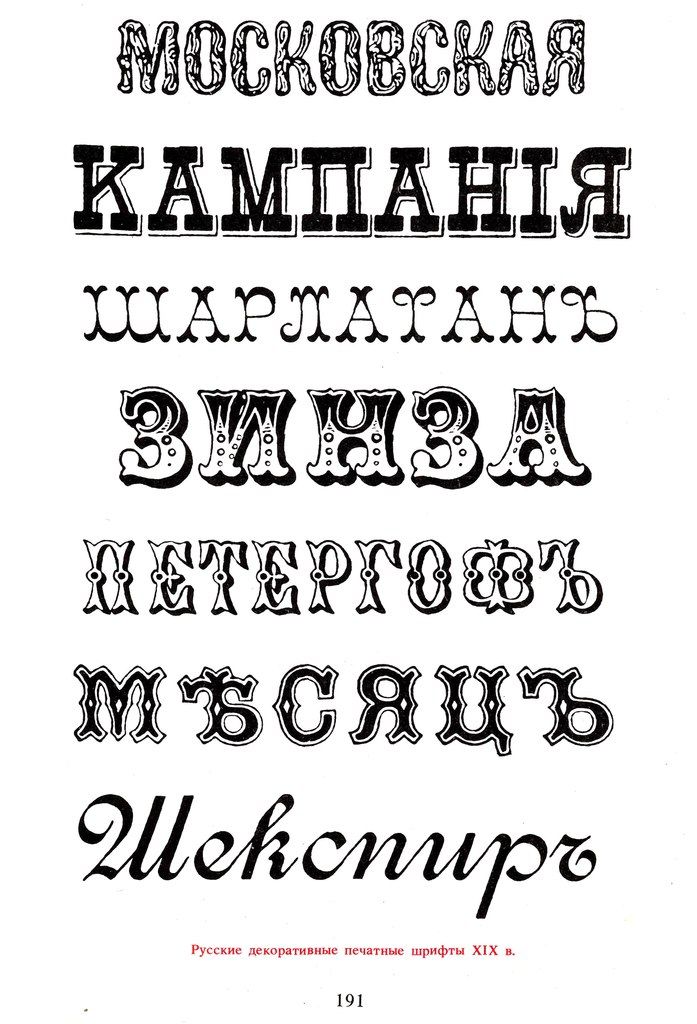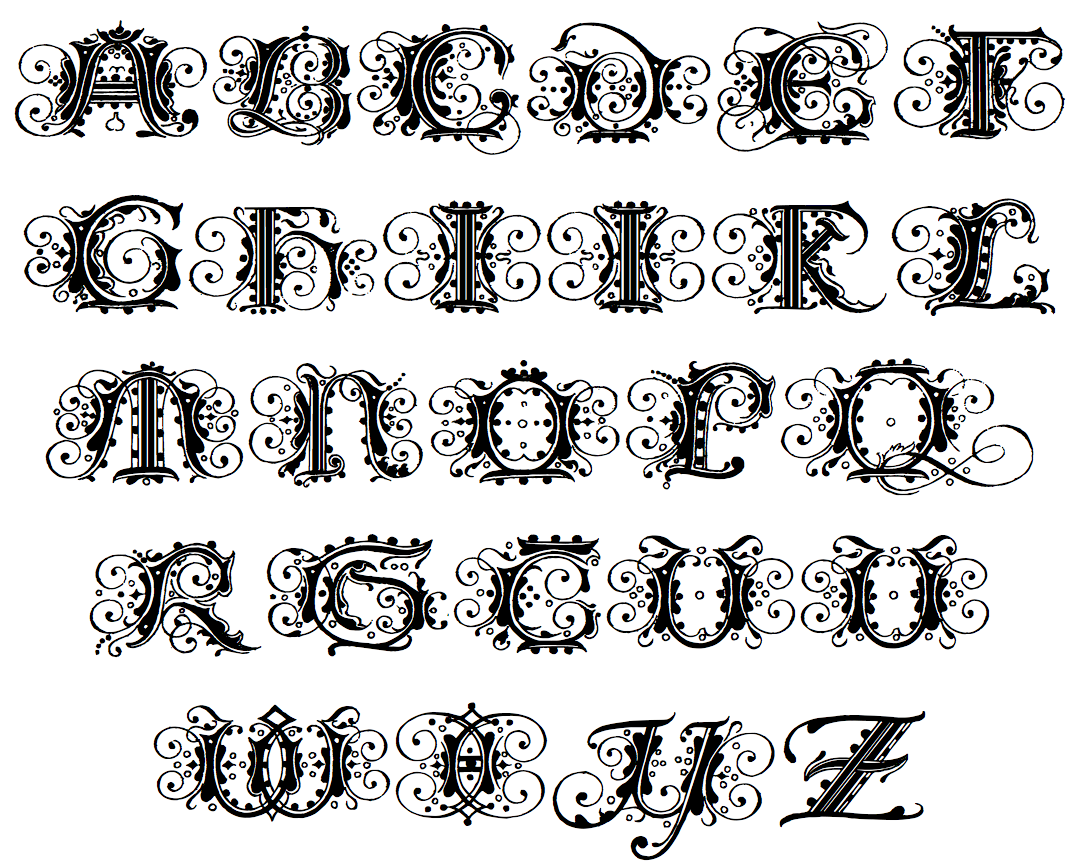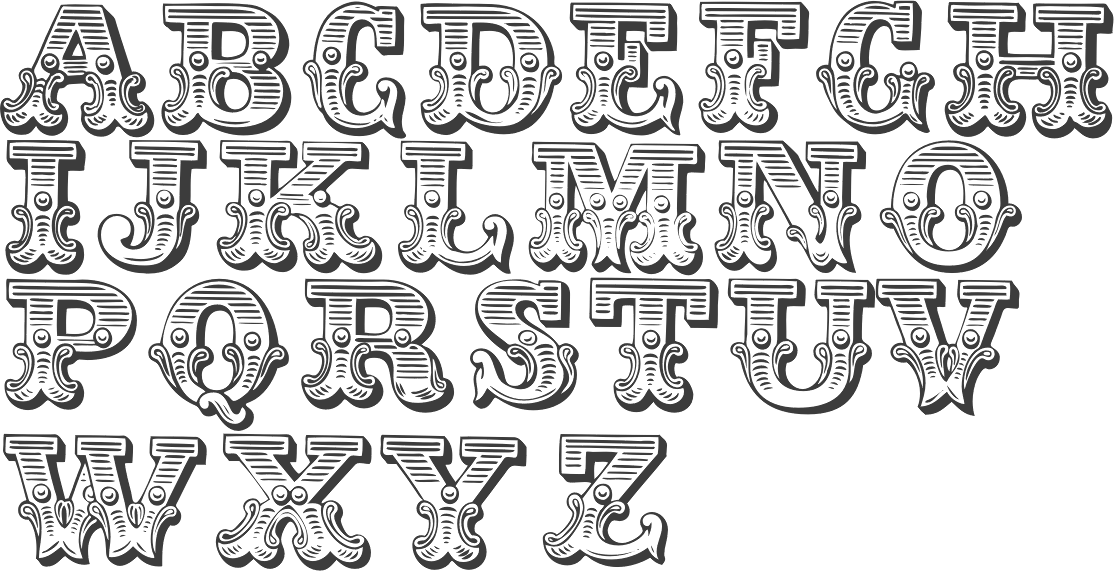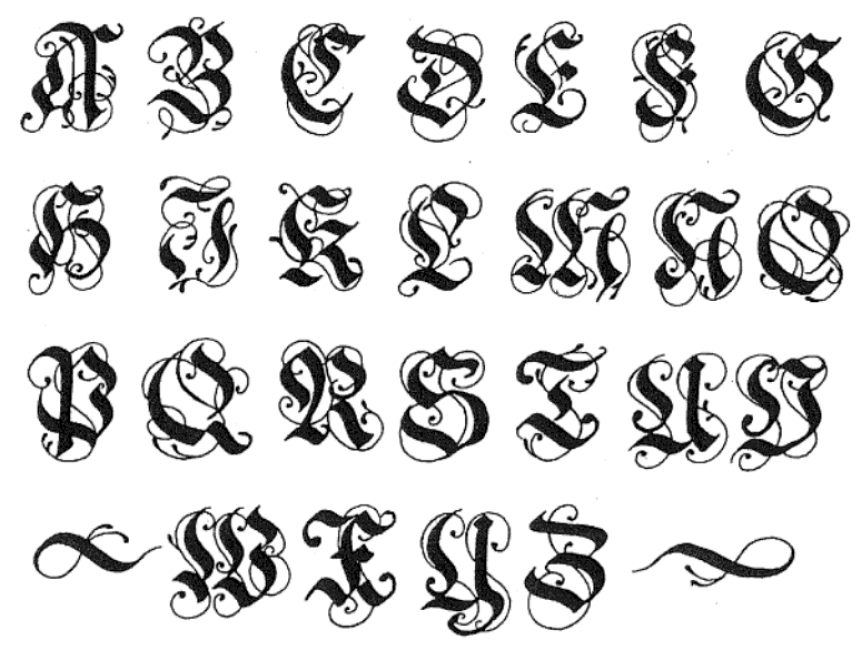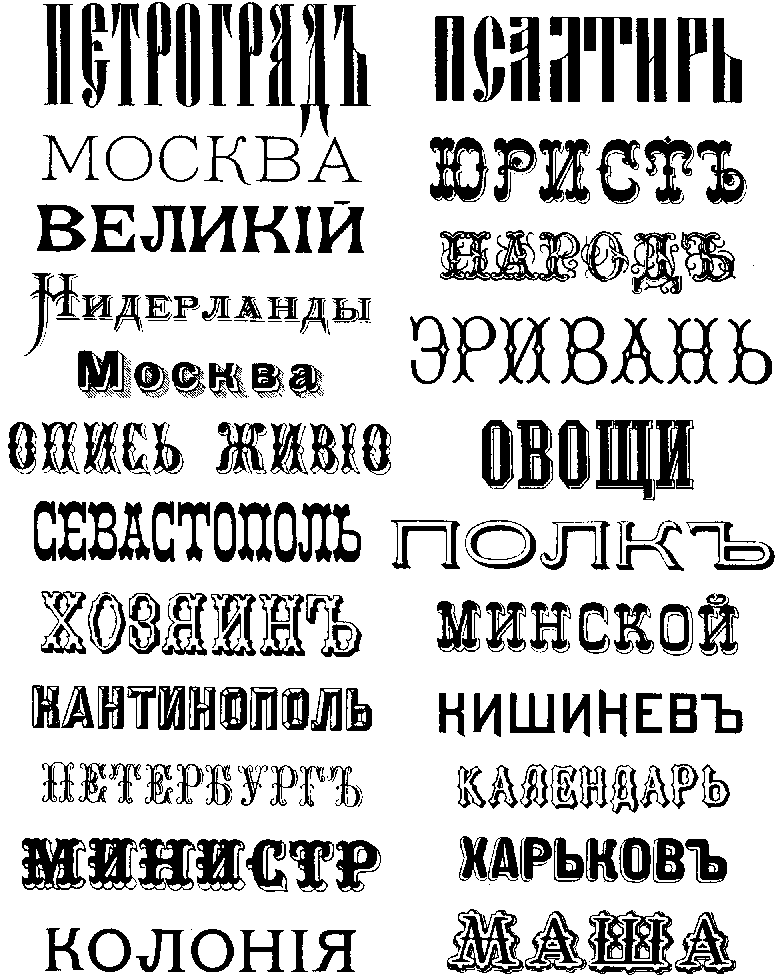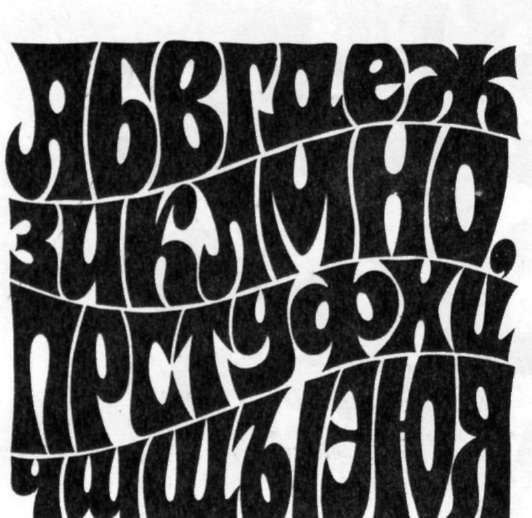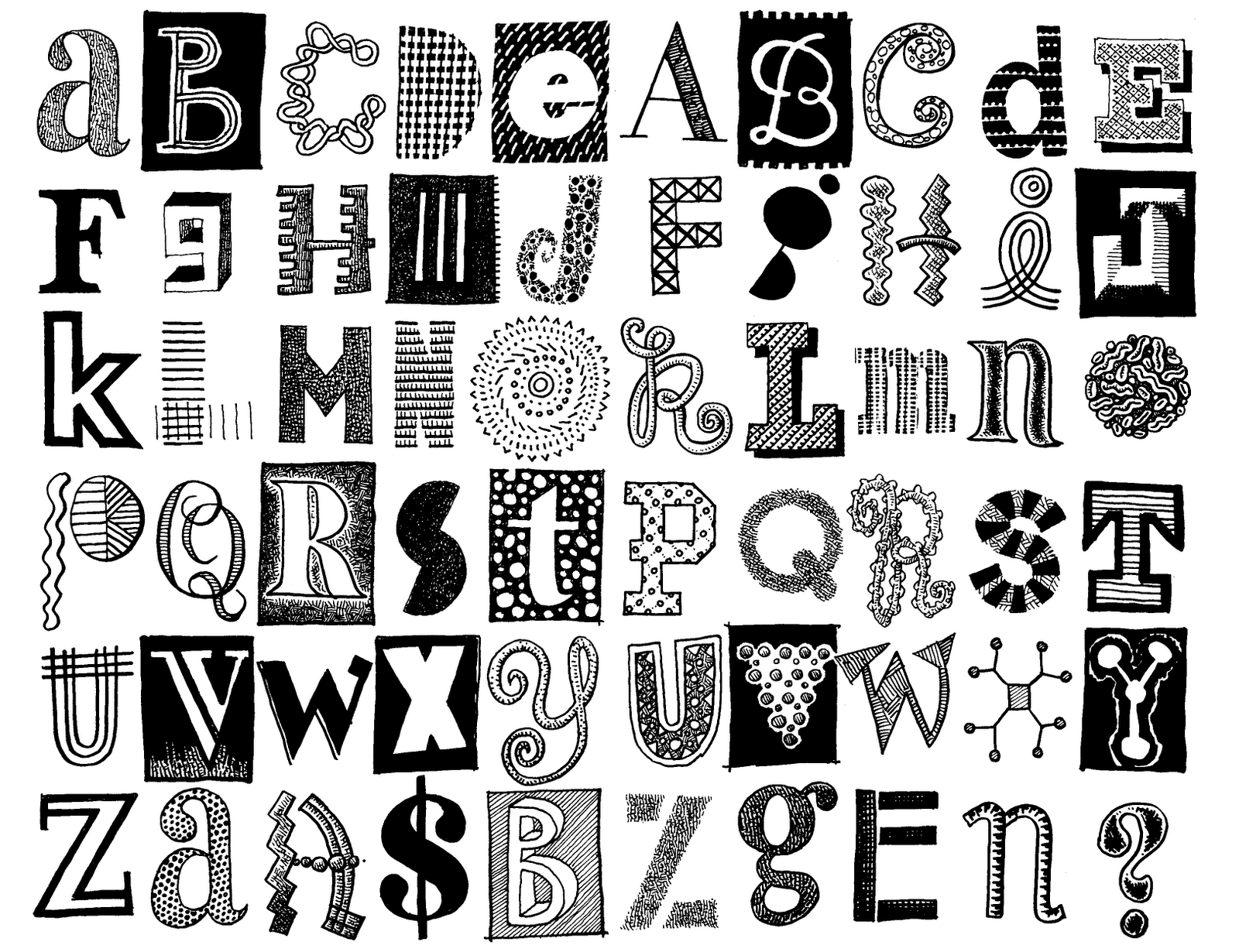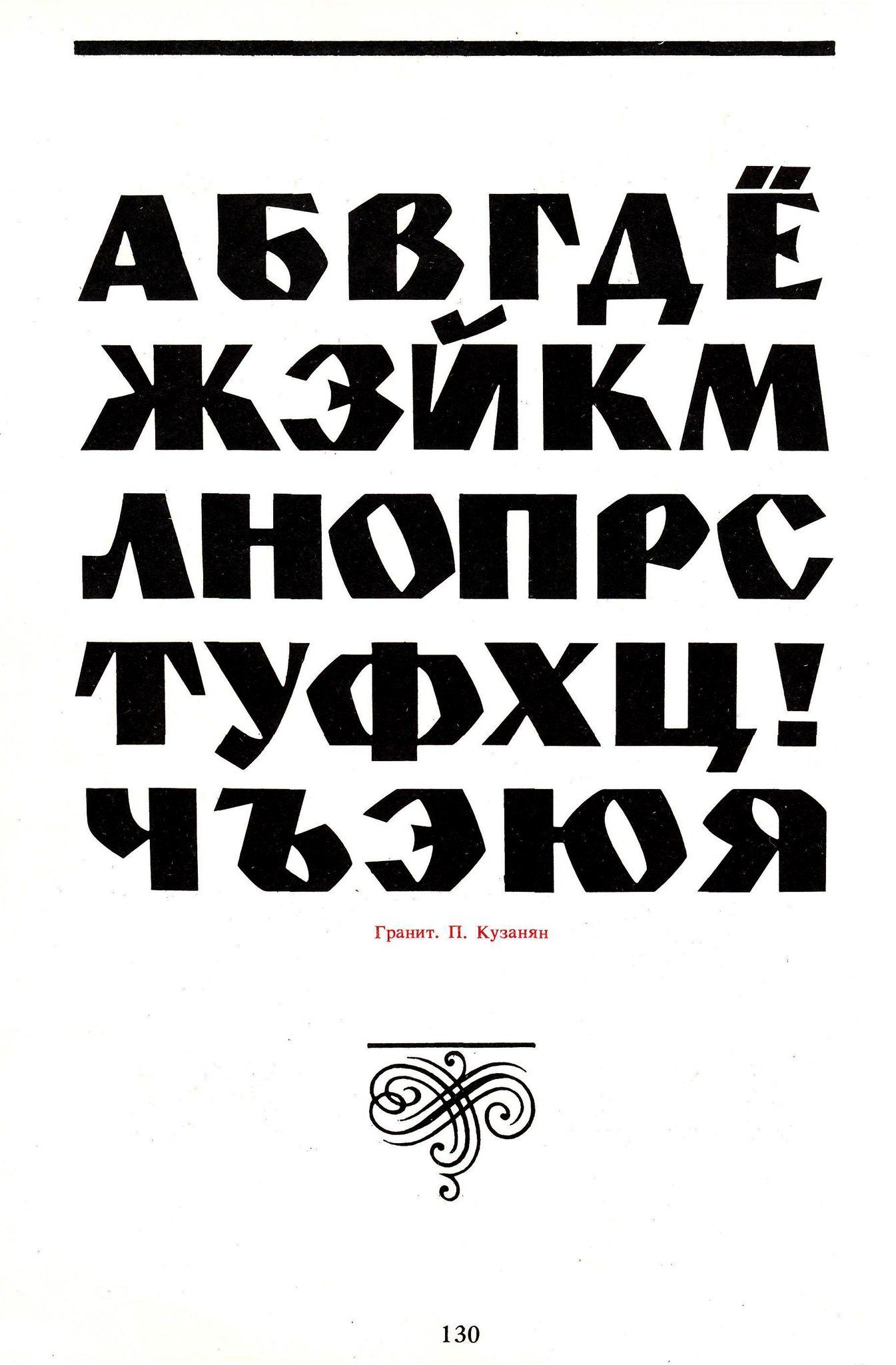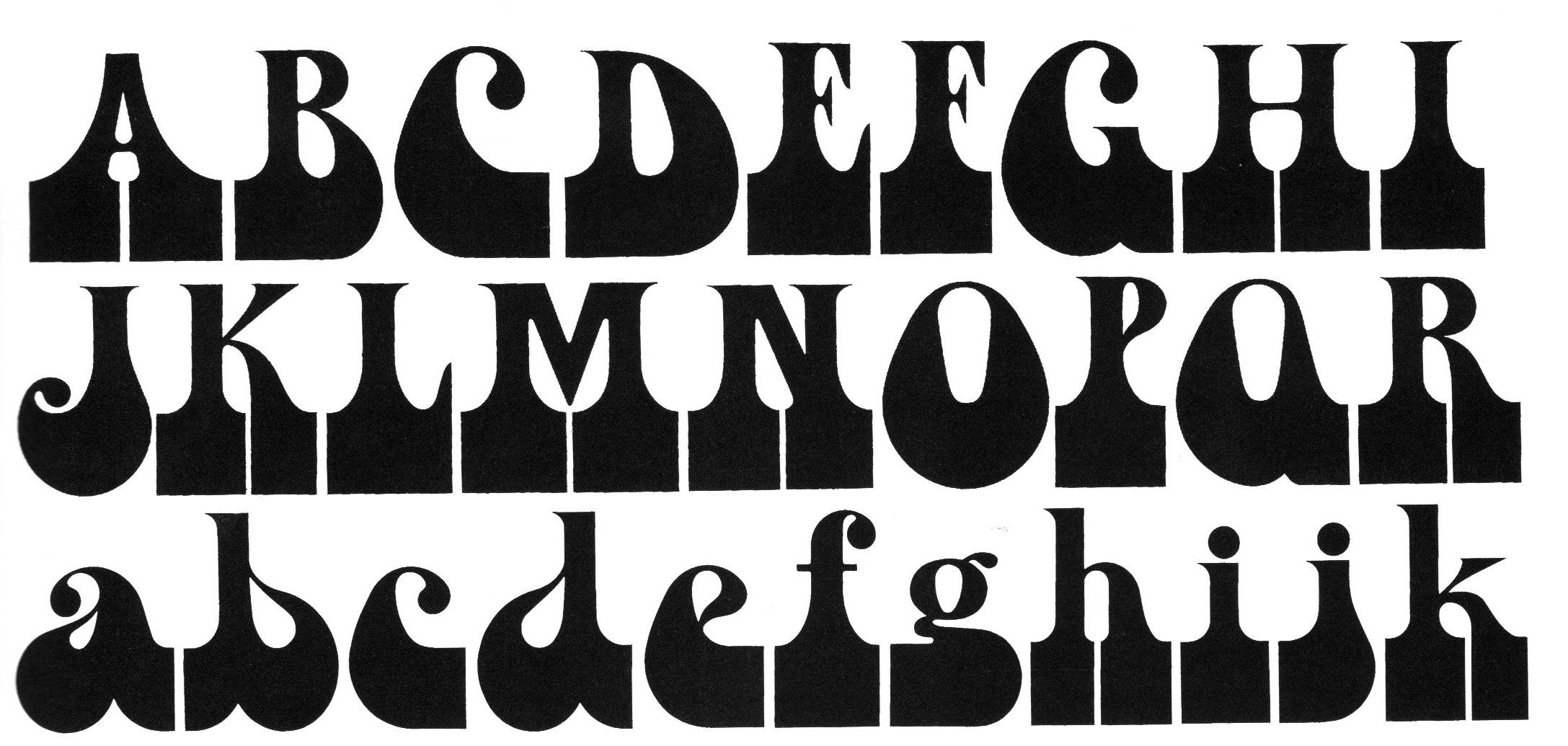
Шрифты оформительские: Декоративные шрифты для художественно-оформительских работ
Шрифты-алфавиты для рекламных и декоративно-оформительских работ 7
Курсив декоративный, с наклонными соединительными штрихами —
стр.
121
Курсив рекламный (переложение латинского шрифта Р. Шпигеля) —
стр. 122
Инициалы: а — по В. Тоотсу; б — декоративные по Р. Шпигелю —
стр. 123
Курсив «шнурковый» (переложение латинского шрифта В. Шенка) —
стр. 124
Шрифт декоративный для исполнения колонковыми кистями
(переложение латинского шрифта) — стр. 125
Курсив рукописный Б. Воронецкого — стр. 126
Шрифты рубленые типа гротесковых и брусковых
Шрифт плакатный, рубленый, прямой, светлый — стр. 127
Шрифт нормальный, рубленый, узкий (по В. Шенку) — стр. 128
Шрифт плакатный, жирный — стр. 129
Шрифт рубленый, прямой, узкий, светлый — стр. 130
Шрифт плакатный, нормальный, прямой, узкий, с овальными
формами — стр. 131
Гротеск прямой, светлый, с острыми окончаниями штрихов —
стр. 132 у
Гротеск прямой, узкий, жирный для средств наглядной агитации
(лозунгов, плакатов) — стр. 133
Гротеск декоративный, узкий, светлый — стр.
134
Гротеск широкий, светлый, с округлыми окончаниями штрихов —
стр. 135
Гротеск широкий, с характерной формой букв «Ж», «К», «Л», «Д»,
«Я» — стр. 136
Гротеск широкий, светлый, с острой формой штрихов и узкой
формой букв «А», «Л», «Д» — стр. 137
Гротеск узкий, светлый, с овальной формой букв «О», «С», «Э»,
«Ф»— стр. 138
Шрифт декоративный бетон — стр. 139
Гротеск плакатный, светлый — стр. 140
Гротеск: а — плакатный; б — декоративный «ленточный» — стр. 141
Гротеск широкий, жирный — стр. 143
Шрифт декоративный кабель-гротеск (переложение латинского
шрифта) —стр. 144
Шрифт брусковый, широкий — стр. 145
Гротеск декоративный — стр. 146
Гротеск «проволочный» — стр. 147
Шрифт брусковый, узкий — стр. 148
Шрифт декоративный эхо, наборный (переложение латинского
шрифта) —стр. 149
Шрифт типа кларендона — стр. 150
Шрифт светлый: а —типа гротеска; б — узкий В.
Паскалева — стр. 151
Шрифт типа ленточной антиквы, прямой, широкий — стр. 152